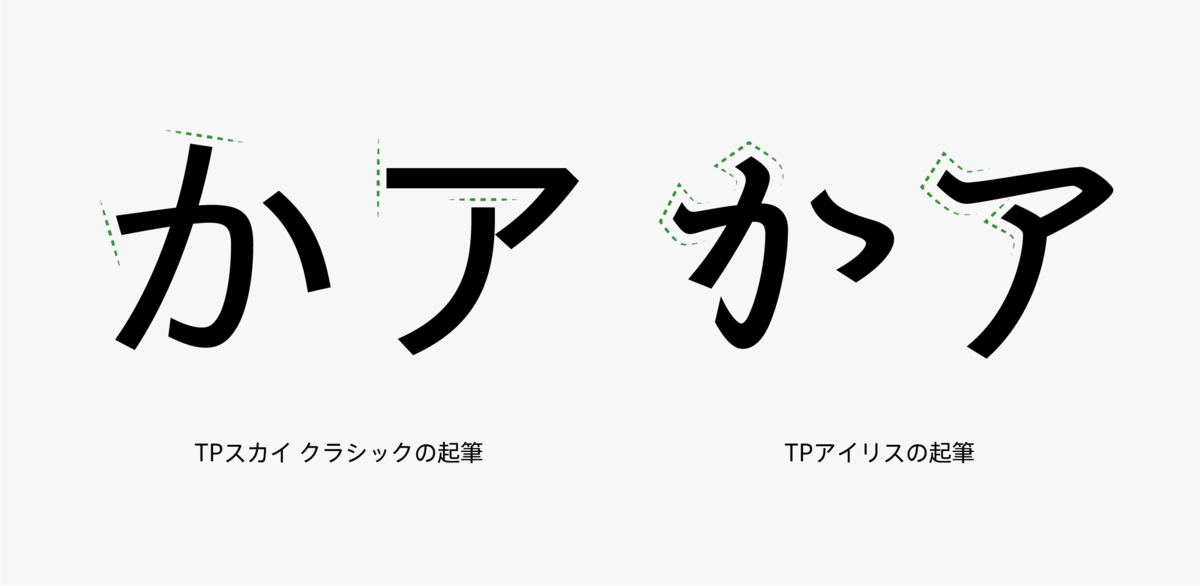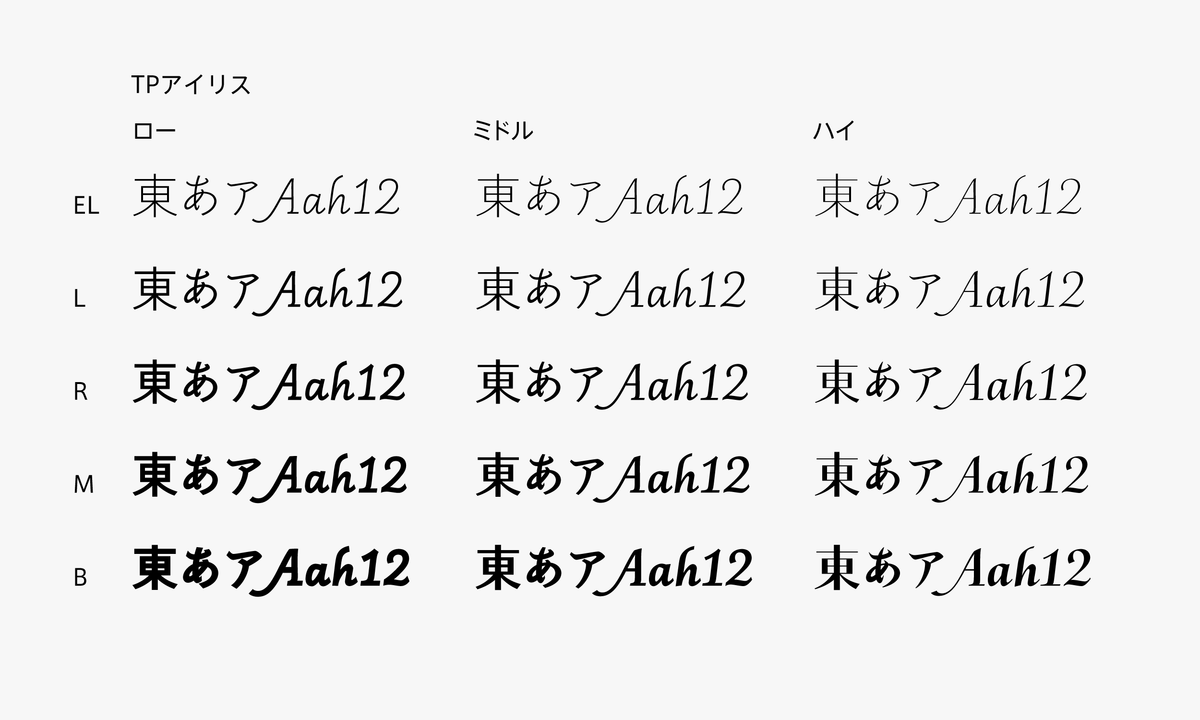
季節の風物を反映した四季フォントプロジェクト -初夏を代表する花、あやめ・かきつばたをイメージした「TPアイリス」の提供開始-
タイププロジェクトは、季節の風物を反映した書体をデザインし、四季折々の空気を文字にまとわせ、日本語をよりゆたかに、より繊細に表現する取り組みとして「四季フォントプロジェクト」を立ち上げた。
第一弾として初夏を代表する花であるあやめ・かきつばたをイメージした「TPアイリス」を発表し、2022年7月28日よりタイププロジェクトのサブスクリプションサービス「TPコネクト」にて提供を開始する。
「TPアイリス」は、古典的な書体に範をとりながら、現代的な用途に適う使い勝手の良い端麗なサンセリフ体。
仮名は優美な平安王朝の仮名を基本にし、欧文は16世紀ごろに発展した典雅な筆記書体をモデルにしている。漢字は、楷書の骨格を現代化した「TPスカイ クラシック」を採用している。
「TPアイリス」のユニークな点は、仮名の起筆に特徴的に表れている。
通常の和文サンセリフは、起筆の形状を切り落としますが、「TPアイリス」は、和様の筆づかいを示す重要な要素として起筆をあつかう。
欧文ではそれぞれのコントラストの特徴に合わせて起筆・終筆の形状や角度を変えている。
ローコントラストでは仮名との統一感を高め、優美な雰囲気を出すためにやや鋭角な先端にしている。
また、ハイコントラストでは筆記具である平ペンの特徴を残した角度や形状を採用した。
「世界規模で急激な変化が続くなか、伝統を育んできた文化が失われる状況はとどまるところを知りません。それに加え、環境破壊による季節感の喪失も深刻です。文化多様性と持続可能性の観点からも四季フォントを意義ある取り組みだと考えています。TPアイリスは、よりどころにした古典に今の感覚を取り入れ、審美的にも実用的にも満足のいく書体に仕上がったと自負しています。詩歌や文芸はもちろん、童話や歌詞など、韻律を大事にしたい詞章の表現に力を発揮することを楽しみにしています」と述べている。
「TPアイリス」は、古典を核に大胆にディテールを刷新したハイコントラスト、広範な用途に安心して使えるミドルコントラスト、そして現代的な表情が新鮮なローコントラストの3つのコントラストに、それぞれ5つのウエイトで構成された、15フォントの書体ファミリーとなる。
・ウエイト:EL(エクストラライト)、L(ライト)、R(レギュラー)、M(ミディアム)、B(ボールド)